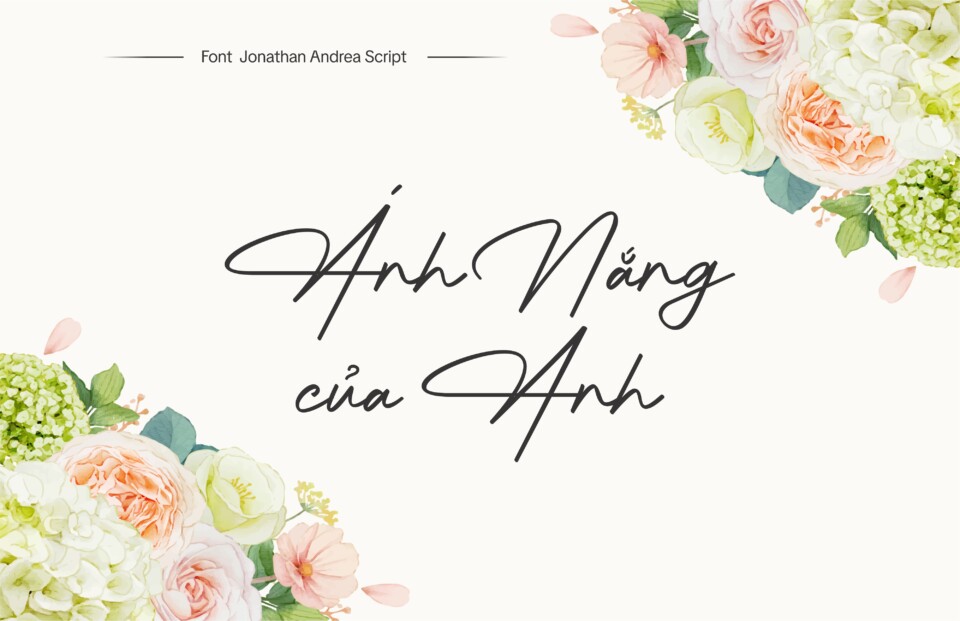
Giới thiệu về bộ Font Việt hóa VN Jonathan Andrea
Trong thế giới đồ họa hiện đại, việc lựa chọn một Font Chữ phù hợp đóng vai trò quyết định đến tính thẩm mỹ của sản phẩm. Font Việt hóa VN Jonathan Andrea là một lựa chọn tuyệt vời dành cho những ai yêu thích phong cách viết tay phóng khoáng nhưng vẫn giữ được nét thanh lịch. Đây là bộ font script tinh tế, được đội ngũ thiết kế tối ưu hóa hoàn toàn cho bảng mã Telex giúp các bạn học sinh và giáo viên dễ dàng sử dụng trong học tập cũng như trình bày bài giảng. Với đường nét mềm mại và uyển chuyển, font chữ này không chỉ giúp nội dung trở nên sinh động mà còn mang lại cảm giác gần gũi, chân thực cho người xem.
Ưu điểm nổi bật của Font Việt hóa VN Jonathan Andrea
Phong cách thiết kế độc đáo và linh hoạt
Font Việt hóa VN Jonathan Andrea sở hữu các đường nét uốn lượn tự nhiên, mô phỏng hoàn hảo nét bút lông mềm mại. Điều này giúp bộ font cực kỳ phù hợp cho các dự án thiết kế thiệp mời, bìa sách, hoặc các banner quảng cáo sự kiện trường học. Tính ứng dụng cao của nó cho phép người dùng kết hợp linh hoạt với nhiều loại font chữ không chân khác để tạo nên sự cân bằng cho bố cục thiết kế.
Hỗ trợ tiếng Việt hoàn chỉnh và miễn phí
Điểm mạnh lớn nhất của Font Việt hóa VN Jonathan Andrea chính là việc khắc phục hoàn toàn lỗi hiển thị dấu câu trong tiếng Việt. Người dùng có thể yên tâm sử dụng mà không lo ngại về vấn đề nhảy chữ hay mất dấu thường gặp ở các bộ font nước ngoài. Việc cài đặt cũng vô cùng đơn giản, tương thích tốt với các phần mềm phổ biến như Microsoft Word, PowerPoint và Adobe Photoshop.